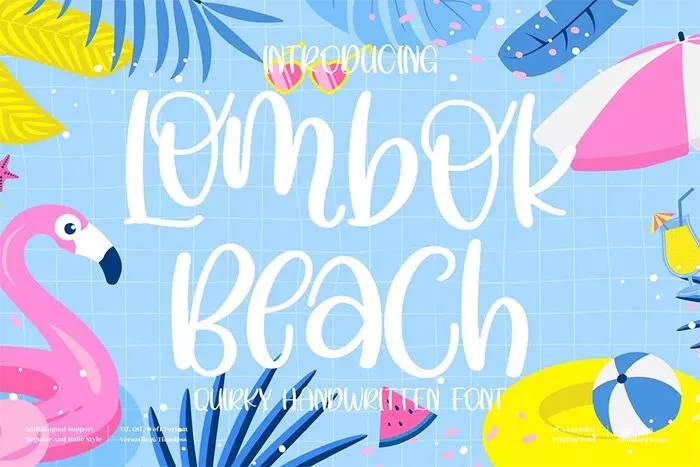
Avete tra le mani il progetto che parla di estate, di mare, di sole e di voglia di vacanze? Oppure più semplicemente state pensato di organizzare quella particolare festa sulla spiaggia e avete bisogno di un buon font per creare il volantino perfetto.
Ecco a voi una bellissima raccolta di fonts gratuiti da usare subito che hanno tutti la caratteristica di essere perfetti se inseriti all’interno di progetti che parlano di spiaggia e di sole: insomma di estate.
Sono 45 summer fonts a vostra disposizione a cui applicare soltanto le vostre idee